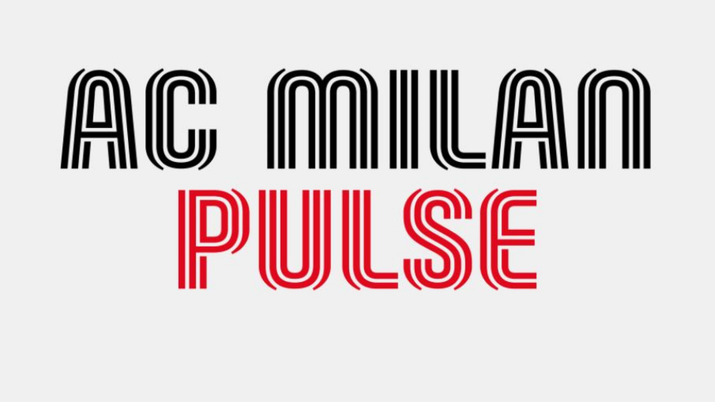
Il Milan si rinnova: i dettagli sulla nuova grafica
ULTIME NOTIZIE MILAN NEWS – I continui progressi del Milan sul campo viaggiano, di pari passo, con l’opera di ammodernamento del club. Secondo quanto riferito da ‘Calcio e Finanza’, i rossoneri hanno depositato un nuovo font per il marchio AC Milan il 13 luglio 2020, con registrazione al 30 dicembre. Una grafica che è già ben visibile nei video di presentazione dei nuovi arrivi e nell’annuncio della formazione titolare prima di ogni partita. Il nuovo font ‘AC Milan Pulse’ è inserito nel progetto di rebranding sviluppato in collaborazione con l’agenzia inglese Dixon Baxi e lanciato nel mese di settembre del 2019.
“Prendendo spunto dalla moda, dai marchi di lifestyle e dalla cultura italiana, abbiamo creato un sistema tipografico audace ma elegante. Immediatamente riconoscibile, cattura la passione che i tifosi del Milan hanno per il loro club“. Queste le parole che si leggono sul sito dell’agenzia londinese.